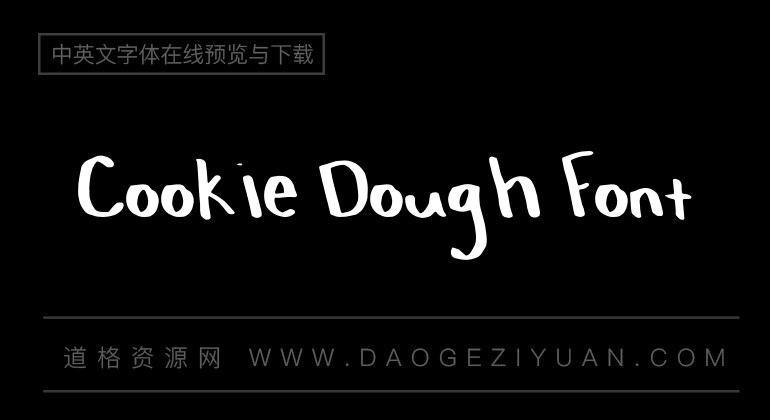
Cookie Dough Font 是一款可爱的手写风格字体,由字母、数字、标点符号组成,非常适合用于儿童书籍、卡片、海报等设计项目。该字体的特点是字母形状圆润、线条柔和,看起来像是手写的卡通字体,同时也具有一定的可读性。该字体可以用于个人和商业项目,并且可以在多种设计软件中使用。内容介绍
Cookie Dough Font是一款非常不错的手写艺术字体,具有很好的视觉感,适合于文化类的宣传设计、商业类品牌的广告和产品包装设计以及个性化文字排版等较多场景。